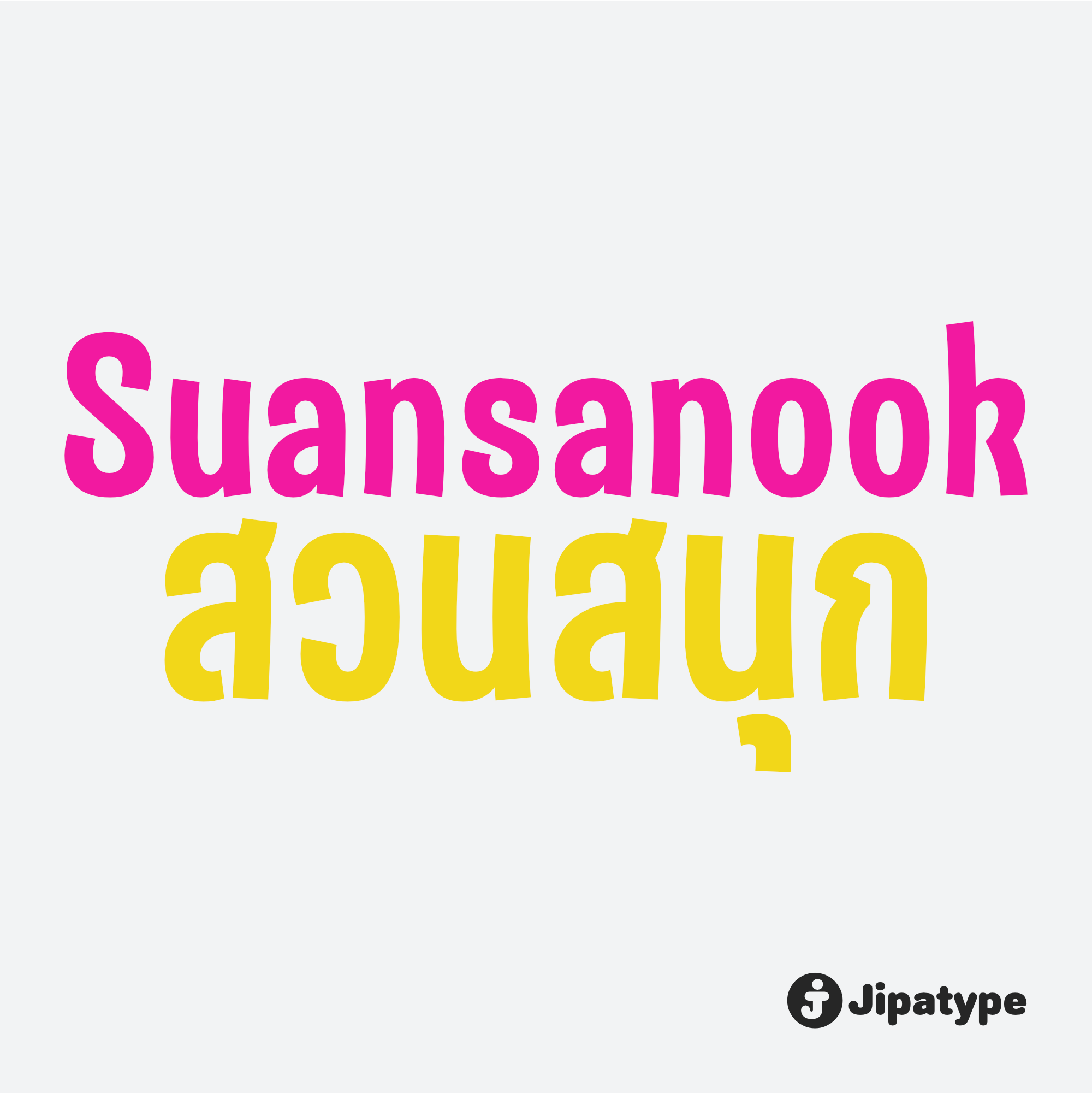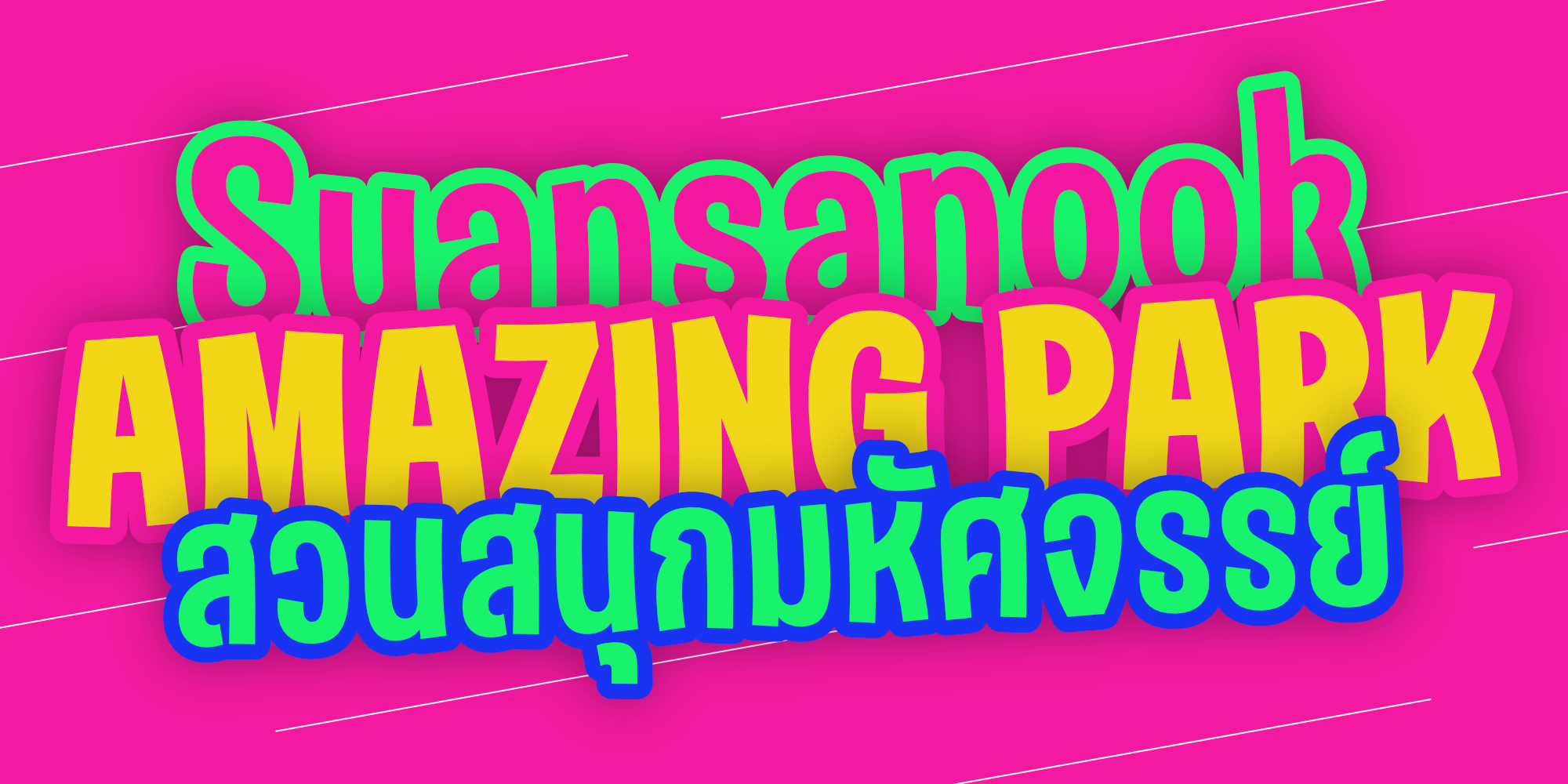
สวนสนุก | Suansanook
ชื่อฟอนต์ : สวนสนุก | Suansanook
Suansanook เป็นอักษรแบบแซนเซอริฟ ความกว้างแคบ นำเอาอักษรแบบมาตรฐานมาดัดแปลงให้เส้นตรงมีความโค้งมากขึ้น ส่งผลให้แบบอักษรดูไม่เป็นทางการ สนุกสนาน มีให้เลือกใช้ถึง 18 สไตล์ รองรับตัวอักษรลาติน 1 และอักษรไทย เหมาะสำหรับสิ่งพิมพ์ต่าง ๆ ทั้งออนไลน์และออฟไลน์ ที่เน้นในเรื่องความสนุกสนาน บรรจุภัณฑ์ขนมขบเคี้ยว สินค้าเกี่ยวกับเด็ก รายการตลก
Creator : อานุภาพ ใจชำนาญ (Anupap Jaichumnan)